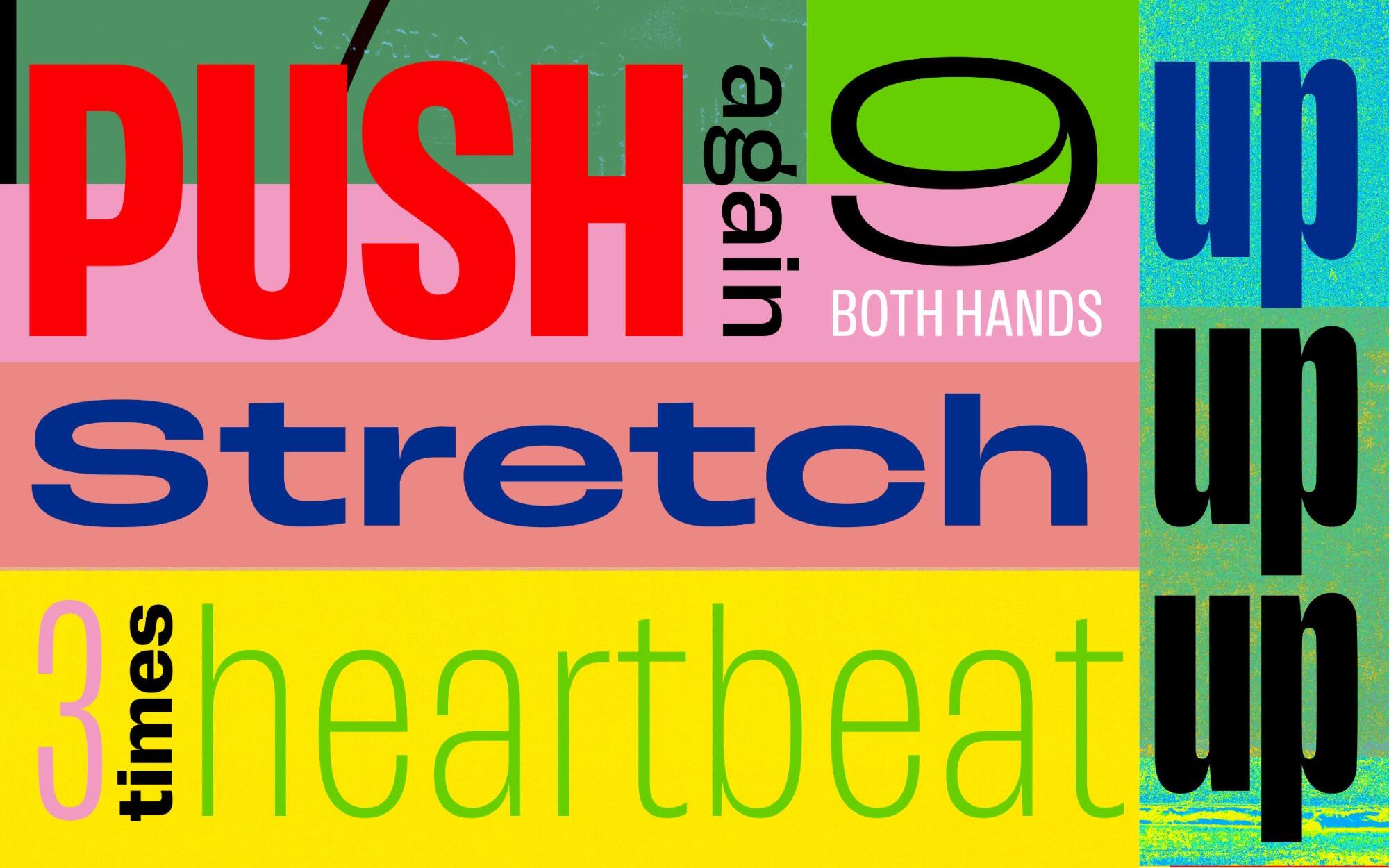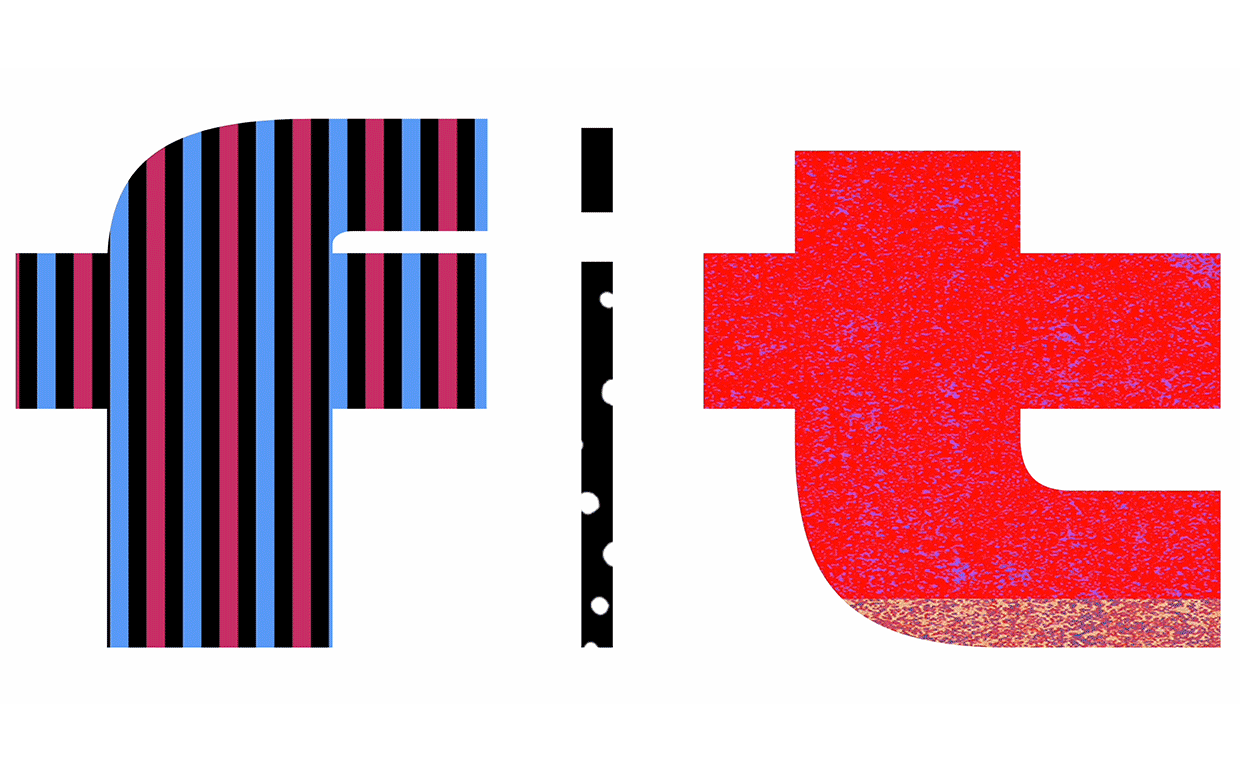
Push ist ein aufrechtes serifenloses Schriftsystem aus acht Schnitten bei sieben Breiten (56 Garnituren). Eine bewusste Veränderung der Kurvenverläufe zwischen XCondensed und XWide von subtilen Kurven in den engen und leichten Schnitten hin zu massiven Kurven und Breiten vereint Eigenschaften aus amerikanischen Gothics und europäischen Grotesken. Diese Übergangsmethode erzeugt durch Form und Gegenform einen Kontrast innerhalb der Familie. Es finden sich Formanklänge aus den ersten einhundert Jahren der Serifenlosen wieder: das schmalfettes G ohne Querbalken ist von Thorowgoods 1830er Seven-Line Grotesque inspiriert, während das kleine a im Geiste der Plak von 1930 erscheint. Im Zeichensatz kann zwischen einem Anglo-amerikanischen Brillen-g, einem dreigeschossigen Grotesk-g sowie einem Dänischen g ohne Schlaufe gewählt werden. Ein weiteres Stylistic-Set ermöglicht es, Akzente und Interpunktion in einem kontrastierenden dünnen Stil zu setzen.